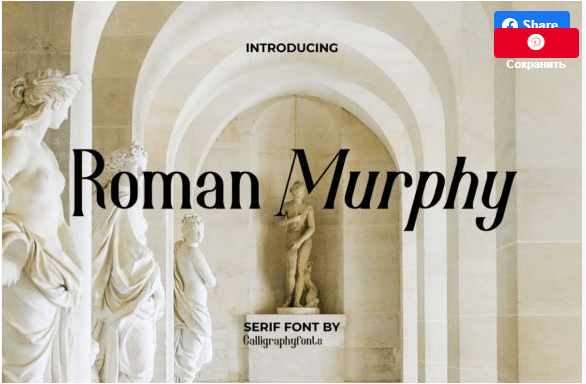
Roman Murphy Font
Roman Murphy - отличный шрифт с засечками. Он впечатляющий, с буквами уникальной формы и, как следствие, легко сочетается с широким спектром творений, требующих особого подхода.